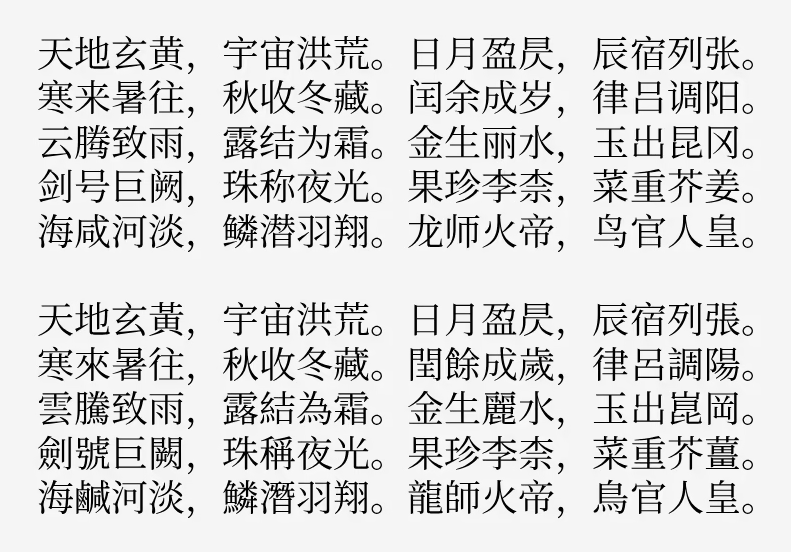
思源宋体是由Adobe 与 Google 联合开发的一款免费开源字体。不同于同系列思源黑体的是,思源黑体是无衬线设计,而思源宋体是衬线设计,所以它更适合印刷和长文本阅读。
宋体的特点是“横细竖粗”,思源宋体在保留这一特点的同时,将笔画末端进行了适度加粗、字腔比例也进行了微调,使其不管是混排还是在屏幕都能保持清晰锐利、高度一致的视觉风格。
思源宋体是2017年4月发布,从简体中文到日文、韩文,再到拉丁字母、希腊字母等字符集,总计超过了45万个字形,是目前开源宋体中最全面的字体之一。
如何选择:
| 需求 | 推荐字体 |
|---|
| 追求传统、印刷书卷气 | 思源宋体 |
| 追求简洁、有高辨识度 | 思源黑体 |
| 做电子书/长文排版 | 优先思源宋体 |
| 做网页/App界面 | 优先思源黑体 |
| 想打造完整品牌字体系统 | 两者搭配使用最佳 |